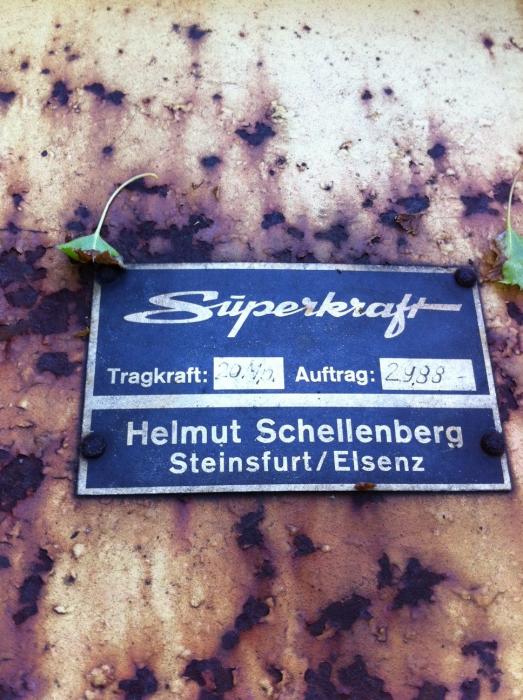
Suche diese Schrift aus den 30-40-oder 50 er Jahren für Pfandhaus Beschriftung....
ich bin schon länger auf der Suche nach der anliegenden Schrift. Wollte so mein Pfandhaus beschriften in so einer
alten Schrift - aber irgendwie finde ich nichts passendes. Hier meine ich Superkraft, leider gibts die Firma nicht mehr....
ja, solche schriften sind vorallem im deutschen schreibstil selten, viele fonts haben leider ein t mit schlaufe oben oder andere amerikanische eigenarten die im deutschen eher untypisch sind. versuch dein glück mal mit den suchbegriffen "retro" und "script" bei myfonts.com
dynascript ist schon ein guter vorschlag.
... oder die Zierfische mal wieder  :-D
Aber irgendwie ist nicht das richtige dabei... glaube langsam ich muss selbst was basteln :-(
Im Prinzip ist das ja auch keine »Schrift«, sondern ein »Logo«. Der besondere Charme entsteht dadurch, dass die Schreibung auf dieses eine Wort zugeschnitten ist - insbesondere was den ersten und letzten Buchstaben angeht. Solche Details findet man in einer Satzschrift logischerweise selten.
Aber wenn du dein Pfandhaus damit beschriften möchtest, wäre es kein Problem einen Grafikdesigner zu beauftragen, der dir einen Schriftzug in diesem Stil maßschneidert.